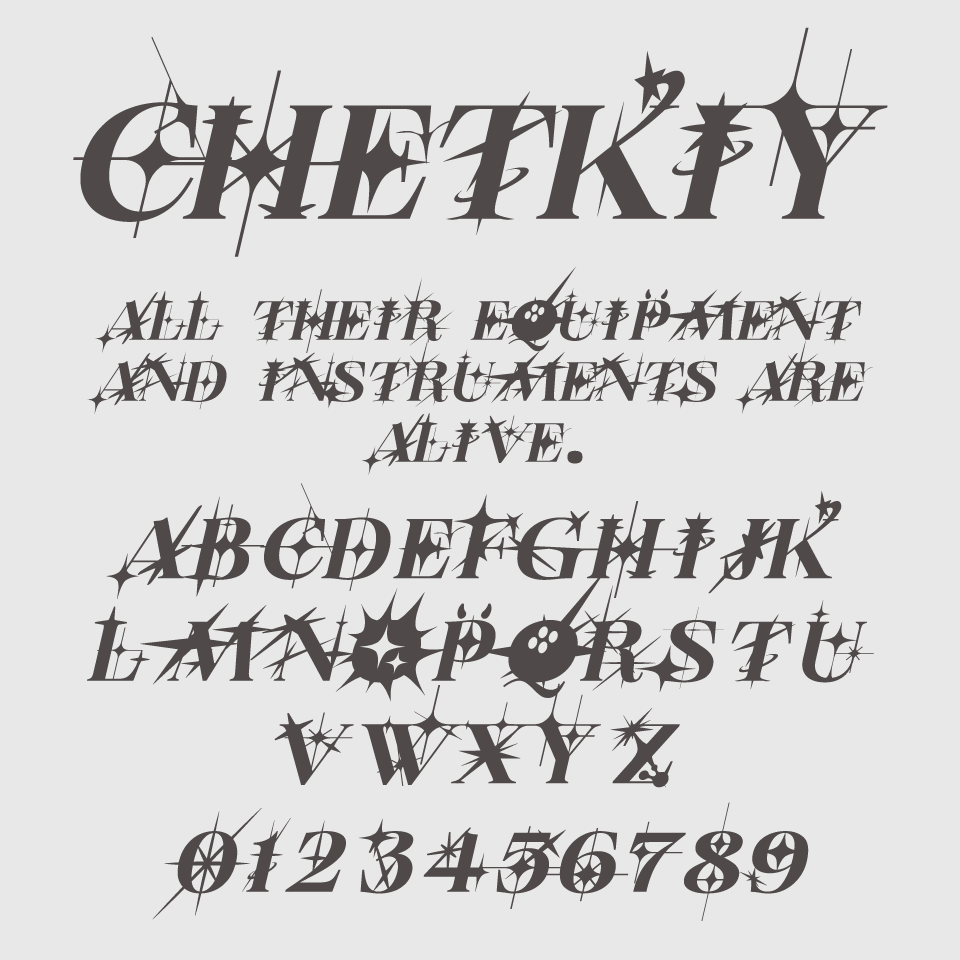
Chetkiyフォントは、トゲのような装飾が全体に施された、異彩を放つディスプレイフォントです。
文字の骨格はクラシカルでありながら、流れ星や月のモチーフが、Y2Kな雰囲気があるデザインです。ユニークなスタイルとグラフィカルな演出が相まって、見る者に強烈なインパクトを残すフォントです。
Y2K以外にも、K-POP風、SFやファンタジー、アンダーグラウンドなカルチャーを感じさせる世界観にマッチし、ポスターやロゴなど、視覚的に印象づけたい場面でぴったりです。読みやすさよりも装飾性を重視しており、タイトルや短い言葉での使用に向いているフォントです。